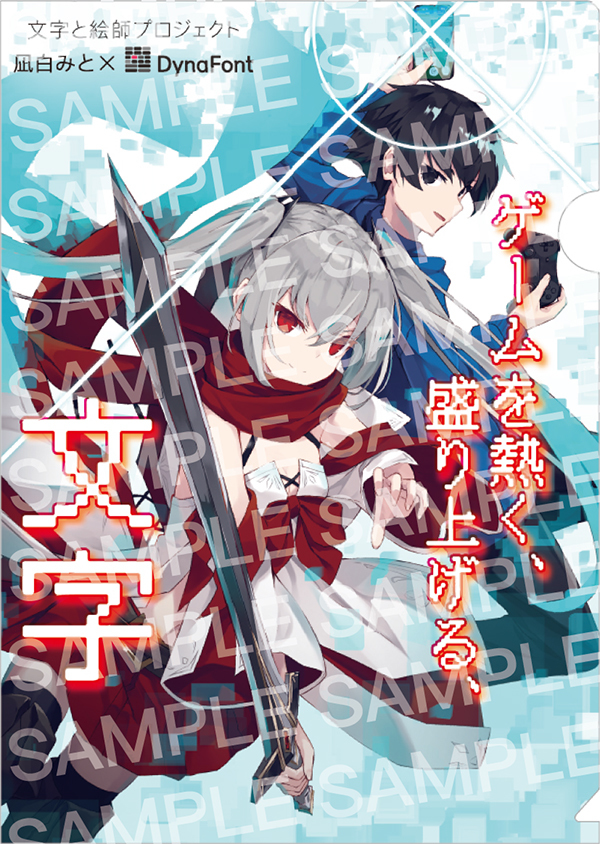
【文字と絵師プロジェクト】人気絵師・凪白みと氏×DynaFontによるオリジナルコラボイラストクリアファイル「ゲームを熱く、盛り上げる、文字」を抽選で100名様にプレゼント
主に文字フォント開発、およびその関連製品の開発・販売・保守を行う、ダイナコムウェア株式会社人気絵師とDynaFont(ダイナフォント)のコラボレーションにより、イラストと書体の魅力を最大限に高め合い、表現する「文字と絵師プロジェクト」をスタートさせた。
文字と絵師プロジェクト第1弾!凪白みと(Mito Nagishiro)氏とコラボレーションしたオリジナルコラボイラストをA4版クリアファイルをプレゼント
プロジェクトの第1弾として、Twitterで25万9,000人以上のフォロワー数(2021年2月現在)を誇る人気絵師・凪白みと(Mito Nagishiro)氏とコラボレーションし、「ゲームを熱く、盛り上げる、文字」をテーマにダイナフォントとのオリジナルイラストを完成させた。
ゲームにオススメの文字を多数取り揃えたダイナフォント
ダイナフォントは、ゴシック体や明朝体などベーシックなフォントから、全ての人に配慮して誰にでも読みやすいUD フォント(ユニバーサルデザインフォント)、楷書体・行書体・隷書体などの毛筆系書体、手書きの温もりを感じさせる手書き風書体、テロップでの使用に適したテロップ書体、そして個性に溢れたバラエティ豊かなデザイン書体まで豊富に取り揃えており、各ゲームジャンル、様々なゲームの世界観に合った文字を使用できる。